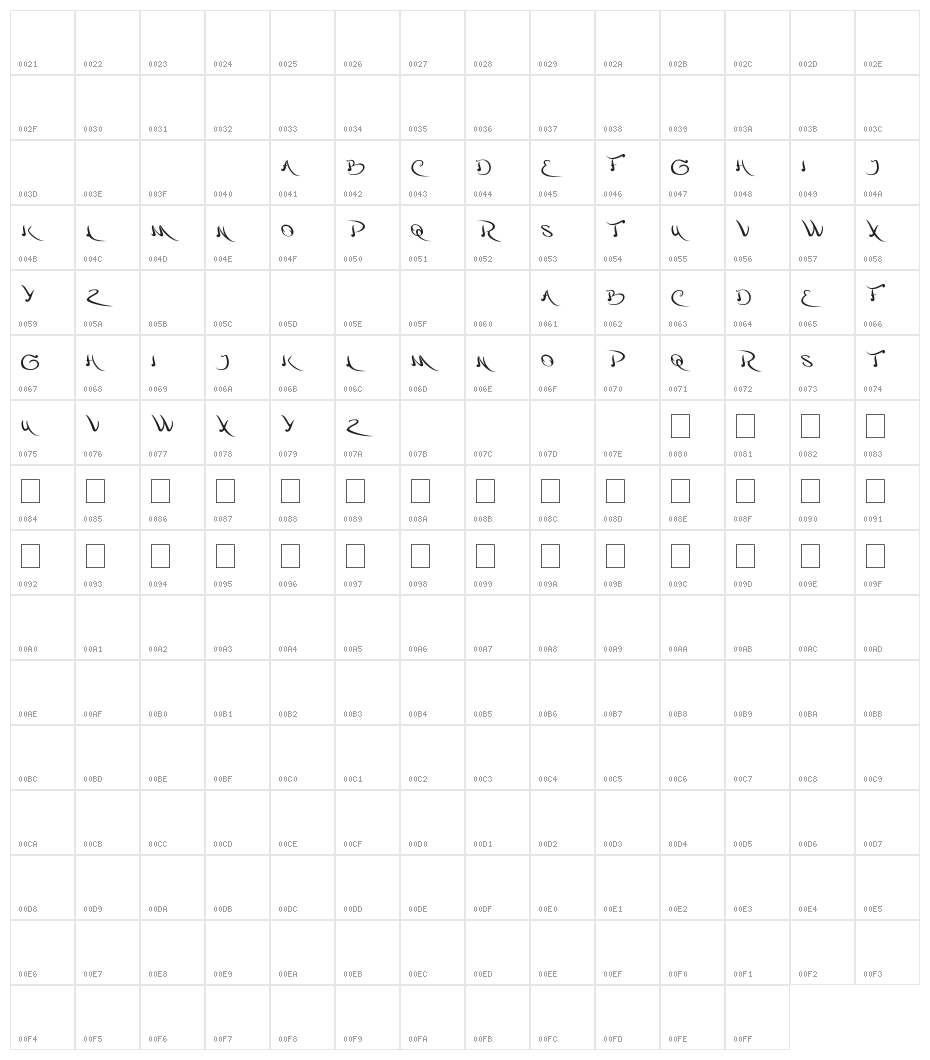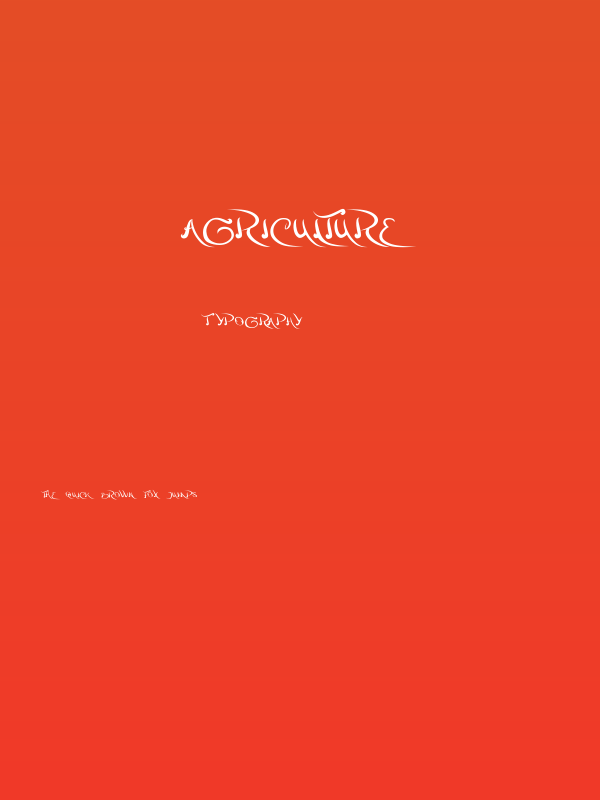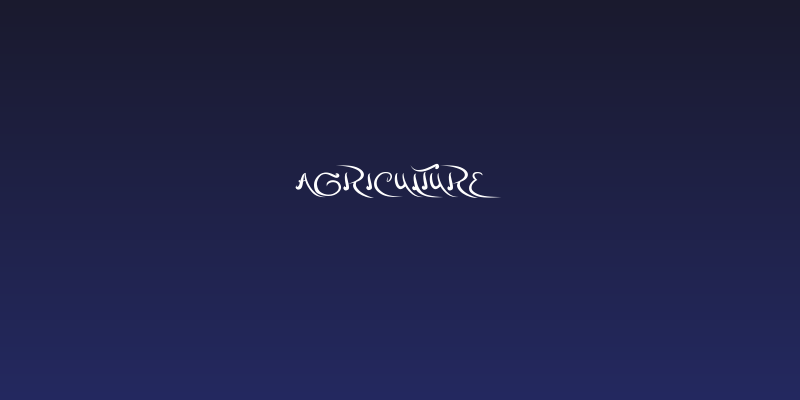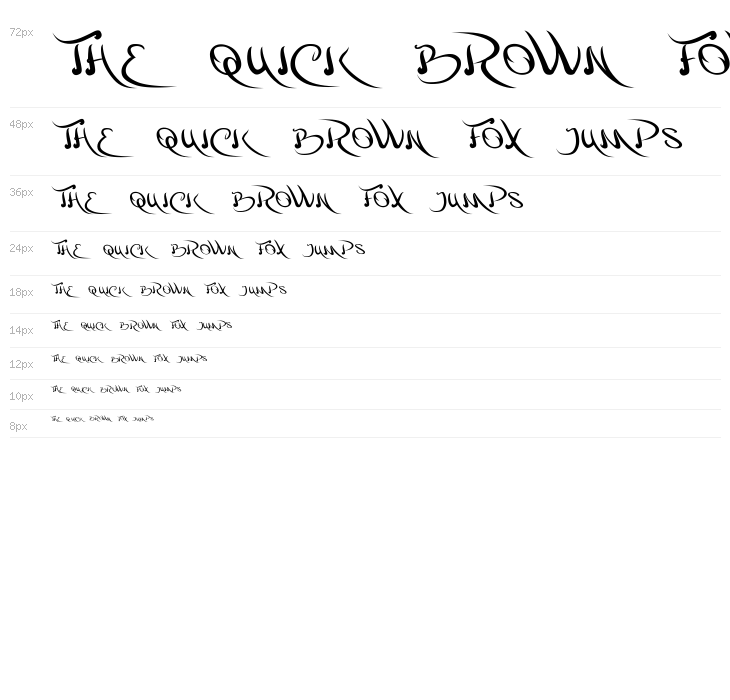
agriculture Font
✎ Calligraphic
| Progetti proposti | Ideal for invitations, posters, branding materials, and any project requiring an elegant and artistic touch. |